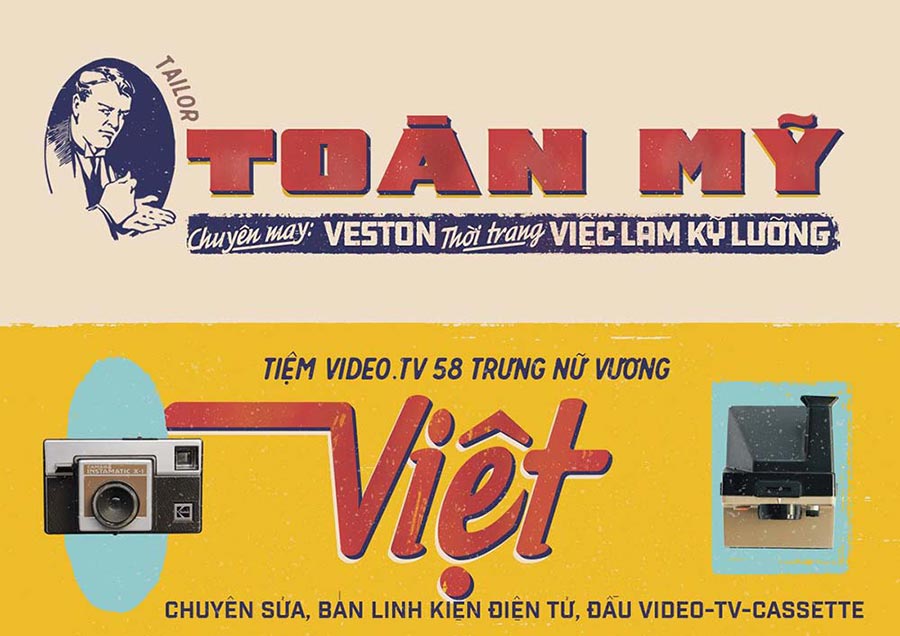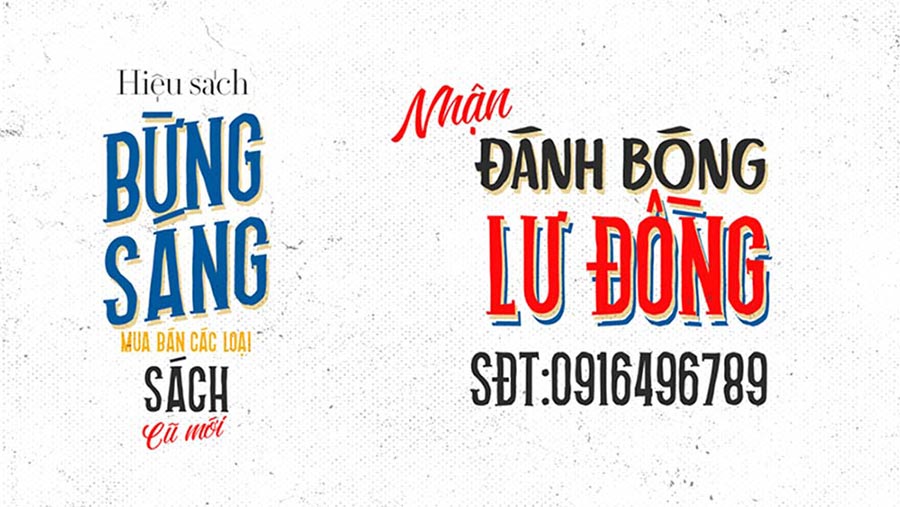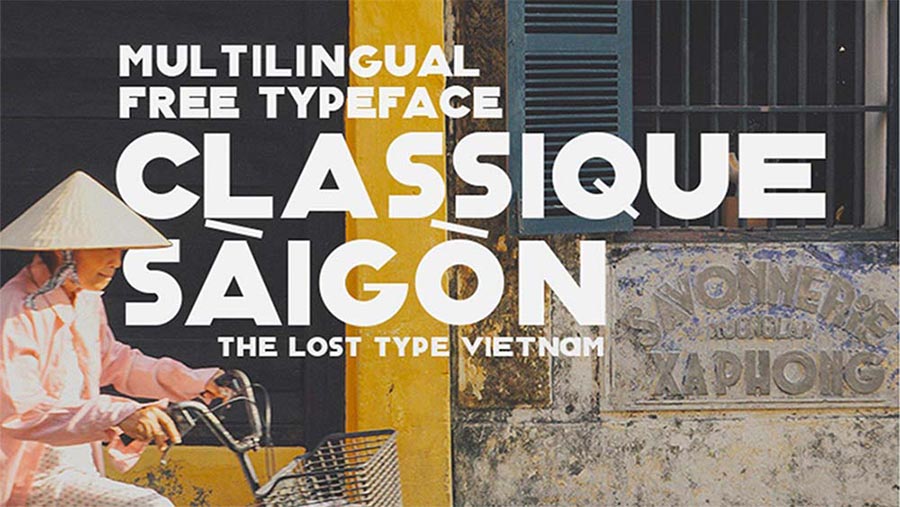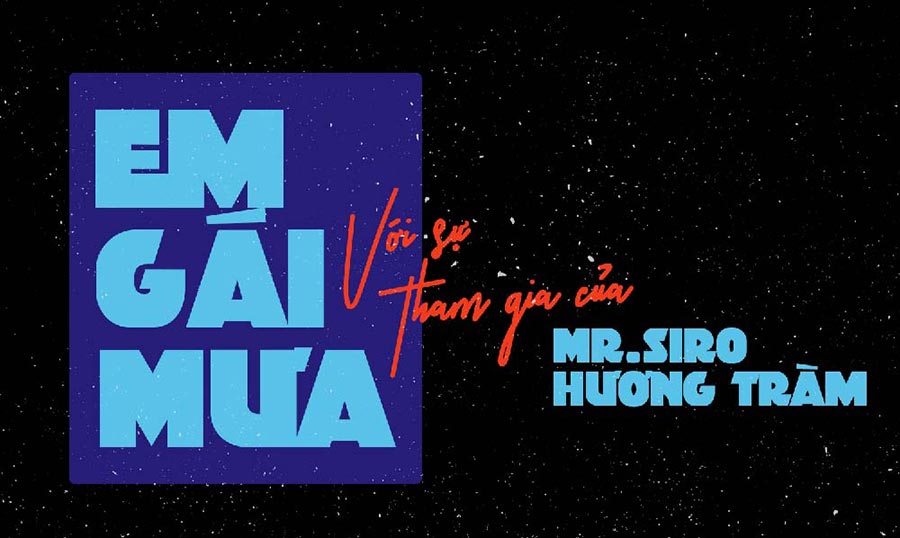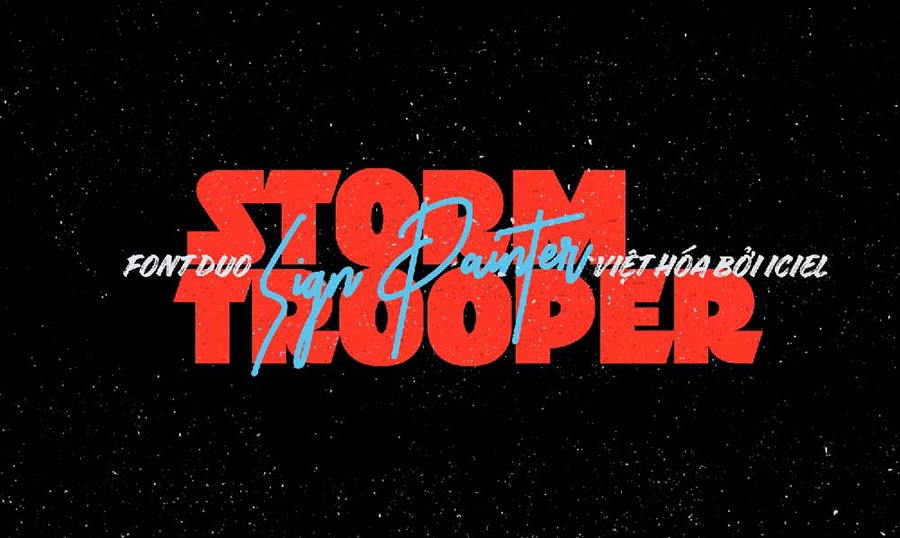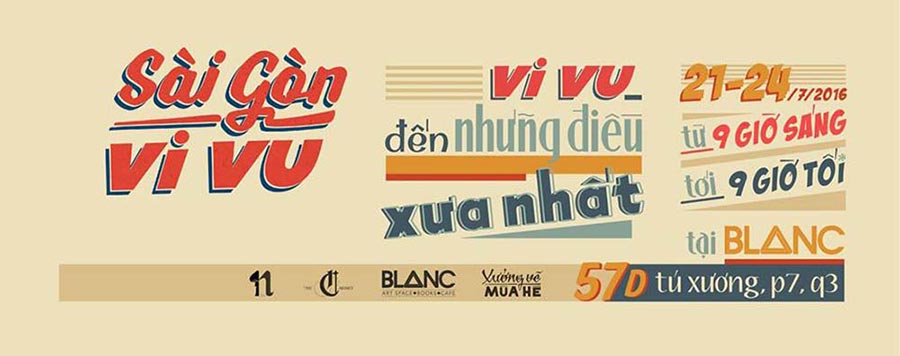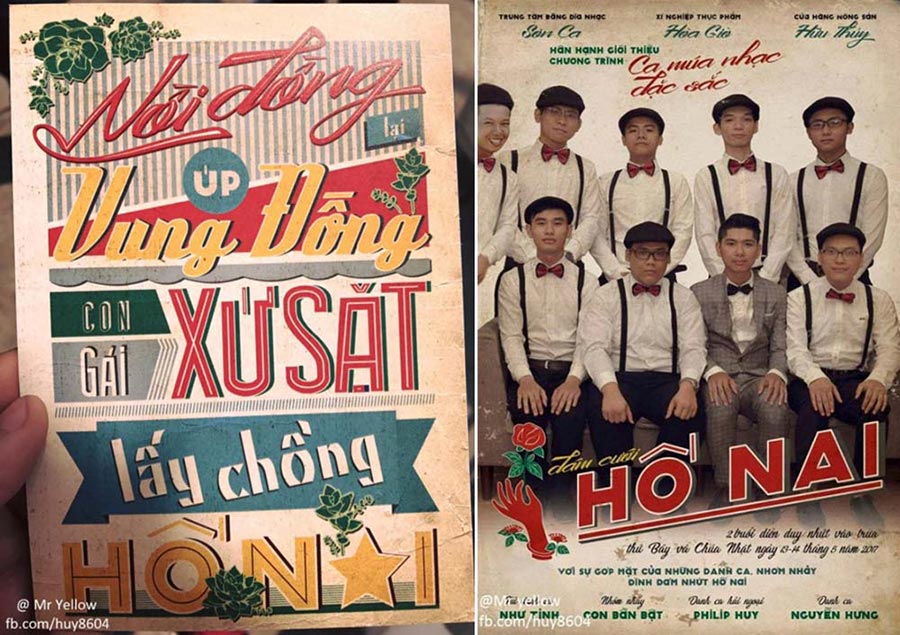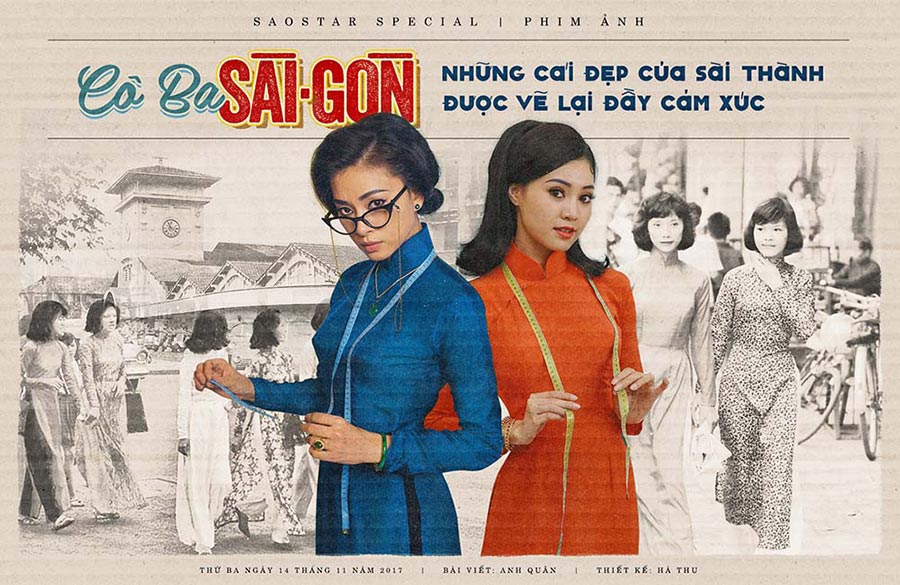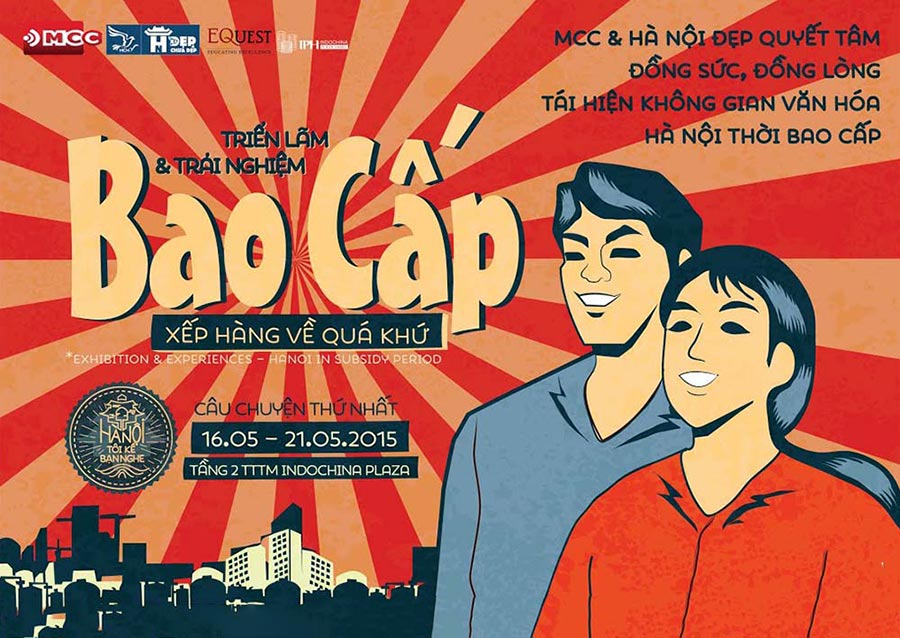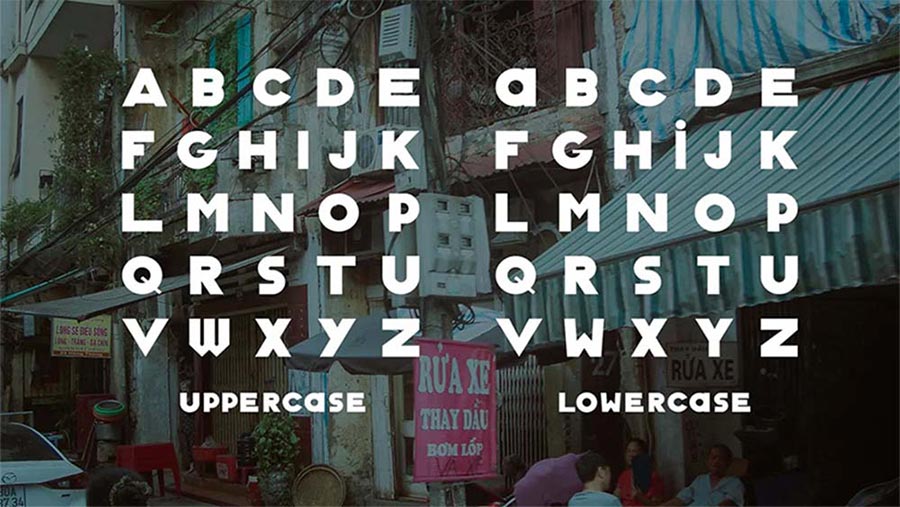
Chia Sẻ Miễn Phí 70 Font Chữ Việt Hóa Thời Bao Cấp Hoài Cổ
Sadesign.vn cung cấp bộ font chữ miễn phí với những thiết kế độc đáo, mang đậm dấu ấn thời kỳ bao cấp, sẽ mang đến cho bạn một kho tàng font chữ phong phú để ứng dụng vào các dự án thiết kế của mình. Hãy cùng khám phá những lý do tại sao bộ font chữ này lại là một lựa chọn tuyệt vời cho các designer chuyên nghiệp.
1. Tại Sao Font Chữ Việt Hóa Thời Bao Cấp Lại Được Ưa Chuộng?
Font chữ mang đậm dấu ấn thời bao cấp là sự kết hợp hoàn hảo giữa yếu tố lịch sử và văn hóa. Những font này không chỉ mang lại cảm giác hoài cổ mà còn giúp truyền tải một thông điệp rất mạnh mẽ về sự thay đổi trong xã hội và con người qua các thập kỷ.
Các font chữ mang phong cách bao cấp có những đặc điểm riêng biệt:
• Nét chữ mạnh mẽ và dứt khoát: Phong cách bao cấp nổi bật với các nét chữ rõ ràng, đậm đà, giúp truyền tải thông điệp mạnh mẽ và dễ nhận diện.
• Phong cách cổ điển, hoài niệm: Các font này mang đậm dấu ấn của thời kỳ cũ, gợi lại ký ức về những năm tháng khó khăn nhưng đầy ắp kỷ niệm.
• Độc đáo và khác biệt: Được thiết kế theo kiểu chữ in ấn, những font này giúp các thiết kế nổi bật và tạo sự khác biệt so với các phong cách hiện đại, trẻ trung.
Sử dụng những font chữ Việt hóa thời bao cấp trong thiết kế sẽ giúp bạn tạo ra một không gian retro đầy hoài niệm, phù hợp với các dự án về lịch sử, văn hóa, các sản phẩm mang tính chất hoài cổ hay thậm chí là các chiến dịch quảng bá với chủ đề vintage.
2. Bộ Sưu Tập 70 Font Chữ Việt Hóa Thời Bao Cấp Từ Sadesign.vn
Sadesign.vn hiểu được nhu cầu của các designer yêu thích phong cách vintage và hoài cổ, vì vậy chúng tôi đã chia sẻ miễn phí bộ sưu tập 70 font chữ Việt hóa thời bao cấp. Bộ sưu tập này bao gồm những font chữ cực kỳ phong phú và đa dạng, từ các kiểu chữ nét đậm, nét mảnh, đến các kiểu chữ cách điệu mang đậm phong cách thời kỳ bao cấp.
Bộ sưu tập 70 Font Chữ Việt Hóa Thời Bao Cấp Hoài Cổ từ sadesign.vn là công cụ không thể thiếu đối với các designer yêu thích phong cách retro, cổ điển, hay các dự án liên quan đến lịch sử và văn hóa Việt Nam. Với những font chữ miễn phí chất lượng, bạn sẽ dễ dàng tạo ra những sản phẩm thiết kế đẹp mắt, ấn tượng và đầy cảm hứng.